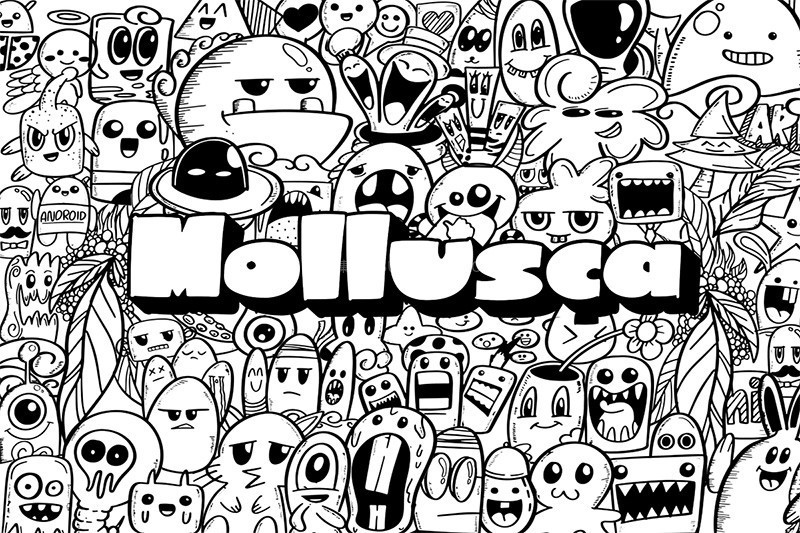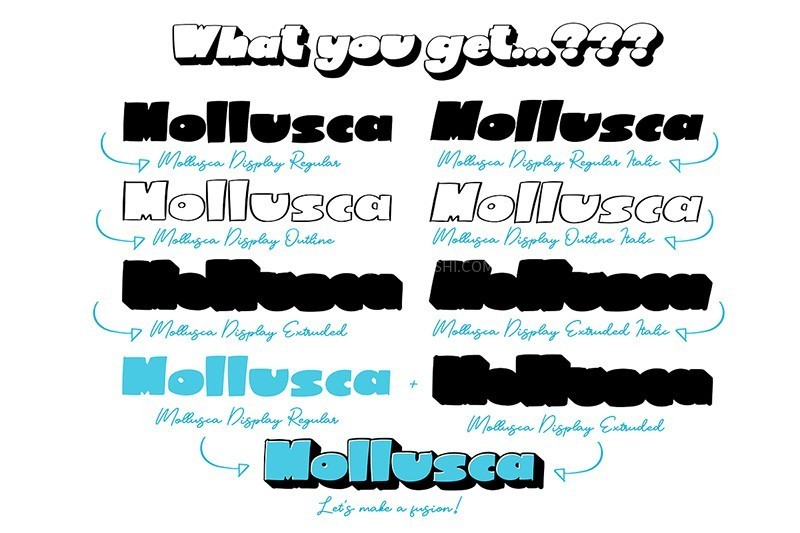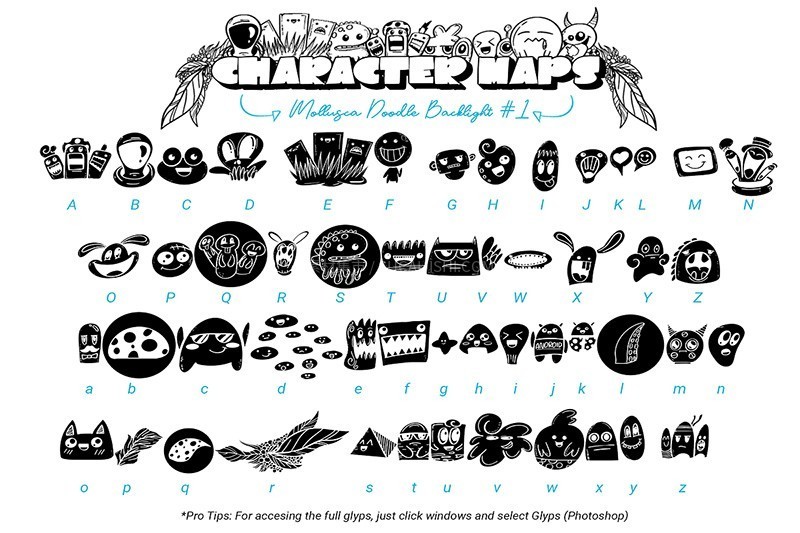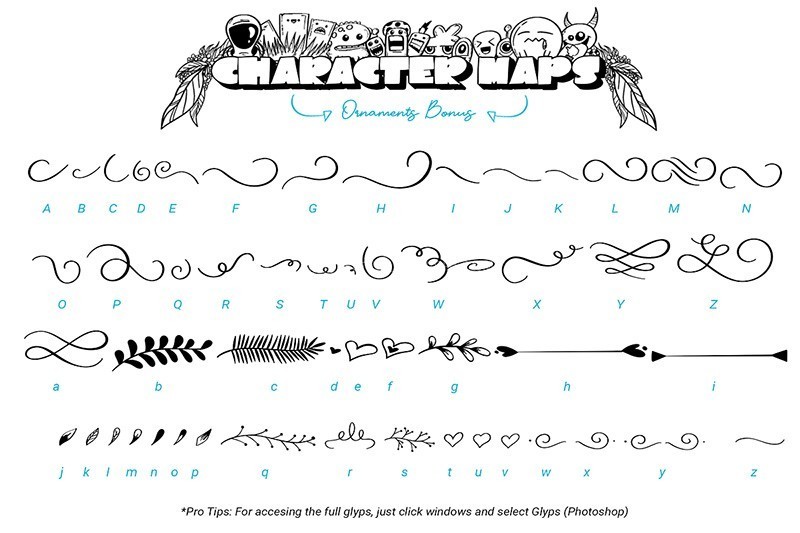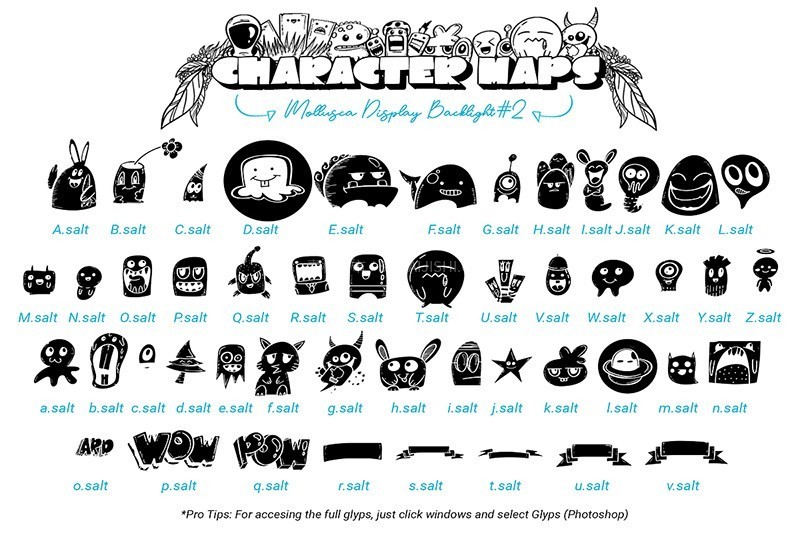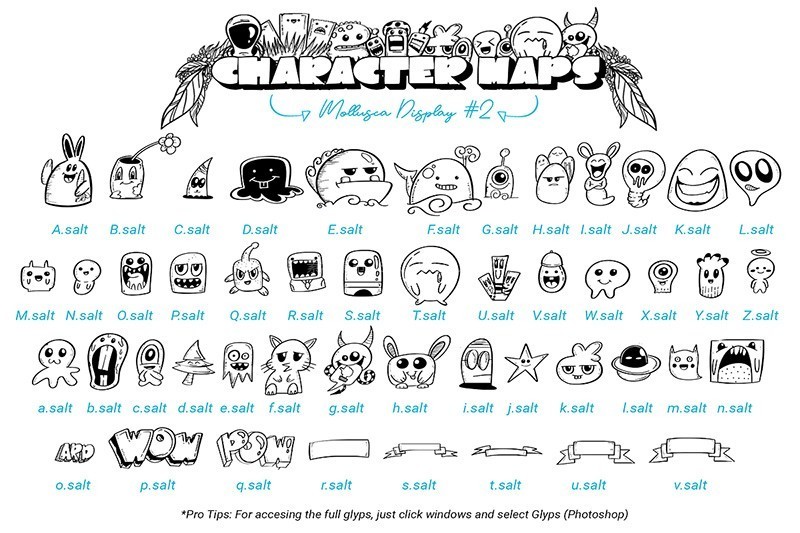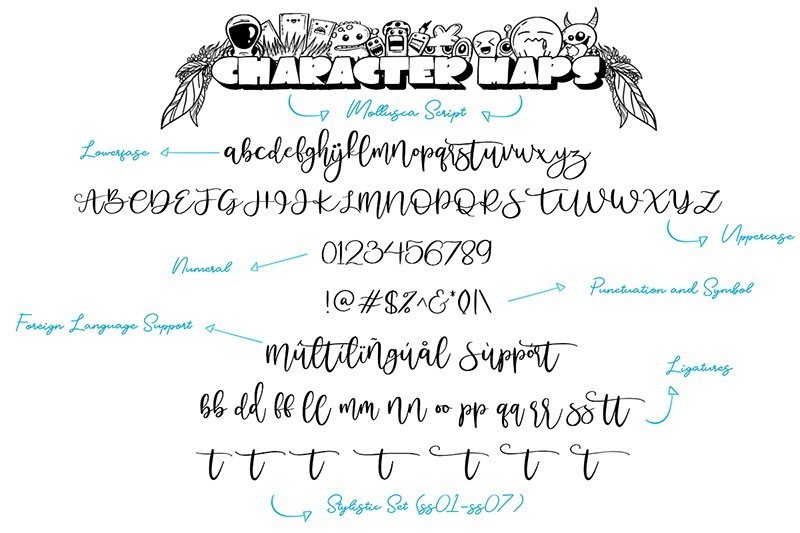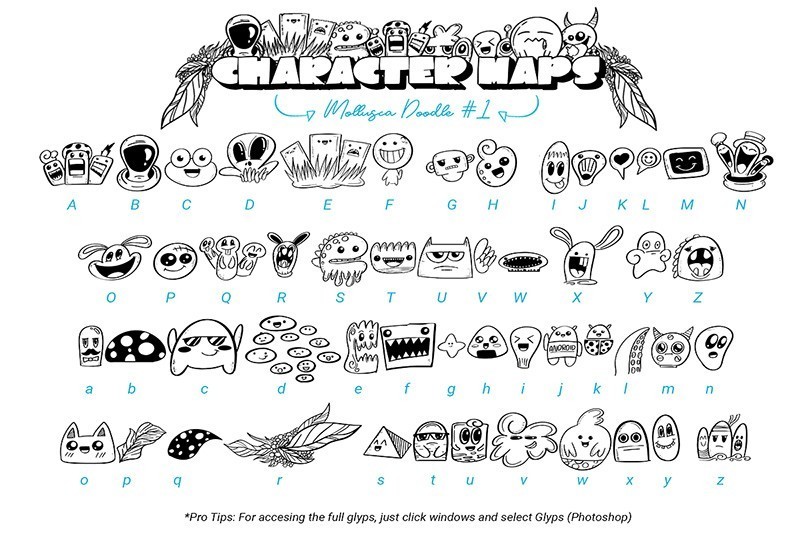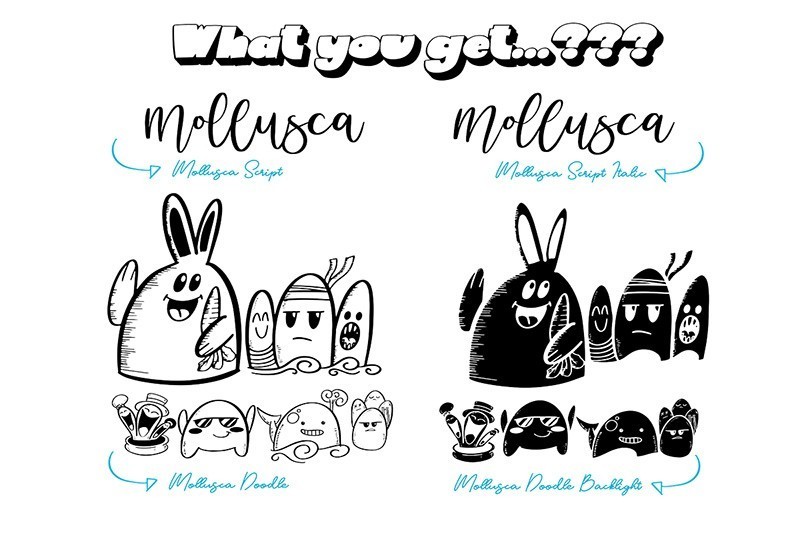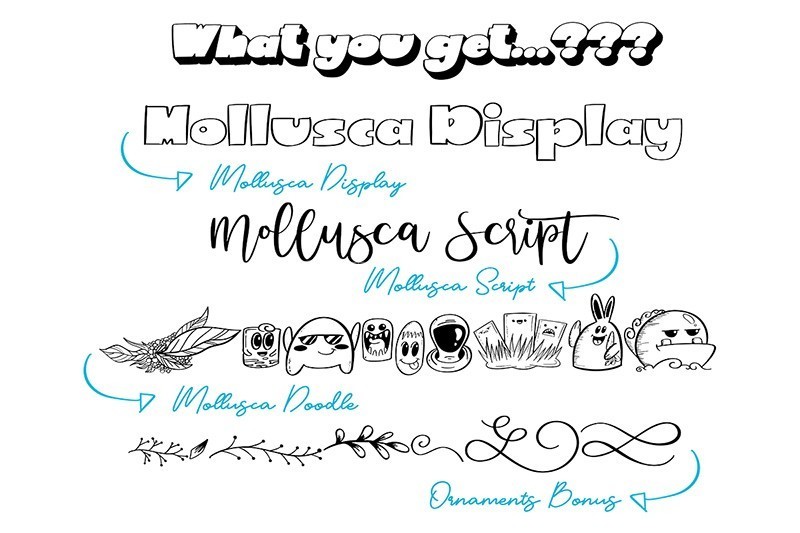
Mollusca涂鸦标志英文字体,附视频教程
Mollusca字体家族包含四种独特且完美互补的风格:Mollusca Display(大胆有趣,3种可自由组合的样式),Mollusca Script(流畅时尚的连笔字体,自带连字),Mollusca Ornaments(酷炫的装饰符号),以及 Mollusca Doodle(独特的涂鸦表情符号字体)。它们可以单独使用,也可以自由组合,轻松打造个性涂鸦logo。